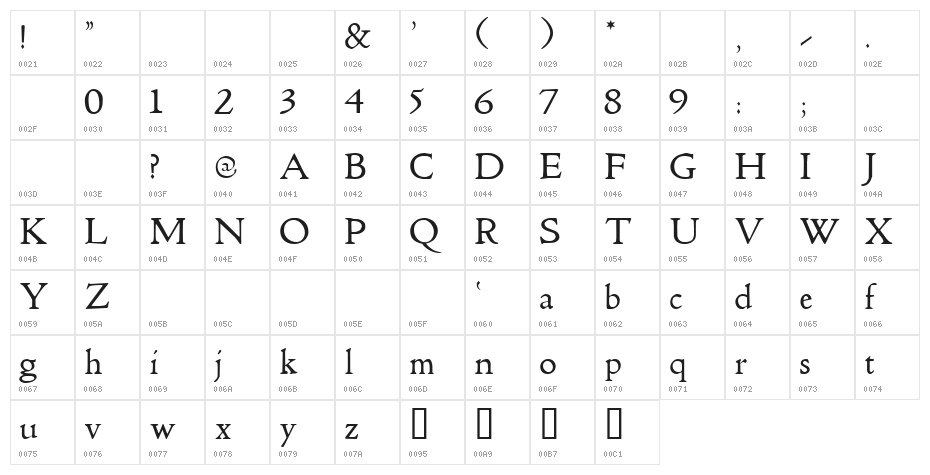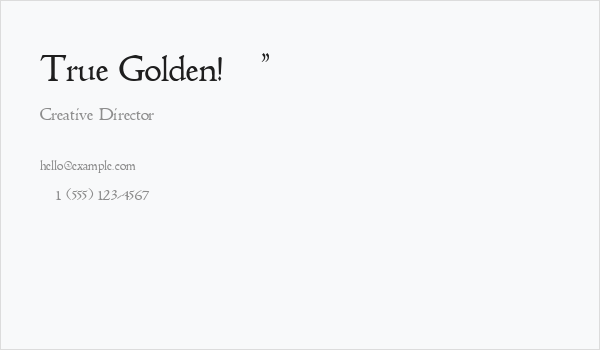
True Golden!" Font
TRUE-GOLDEN Litere mari
TRUE-GOLDEN Litere mici
TRUE-GOLDEN Alte caractere
| Nume | True Golden!" |
| Proiecte propuse | Ideal for use in formal invitations, book covers, editorial design, and branding projects that require a touch of elegance and tradition. |